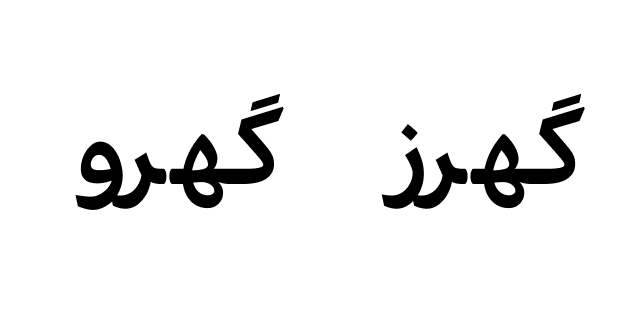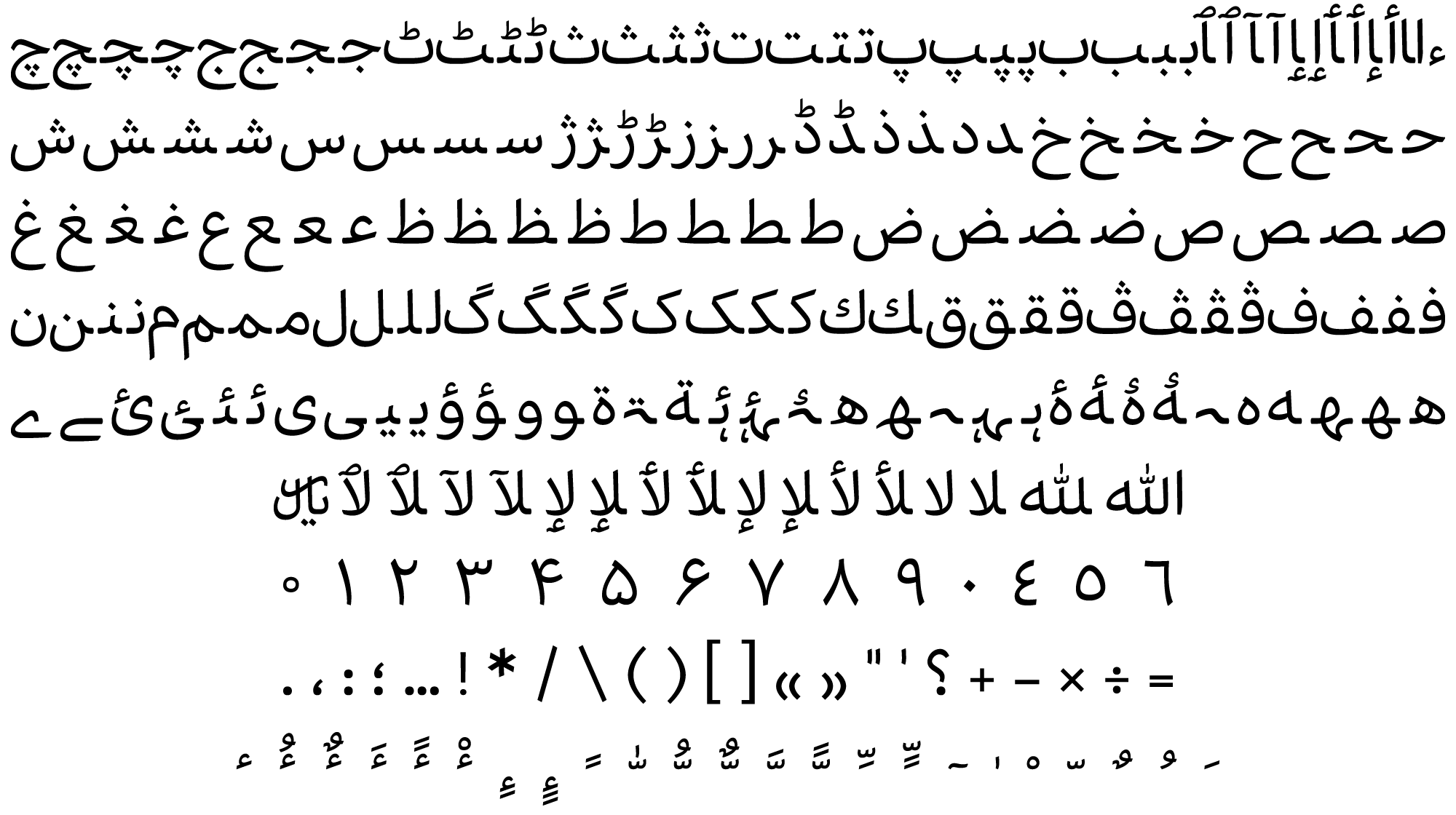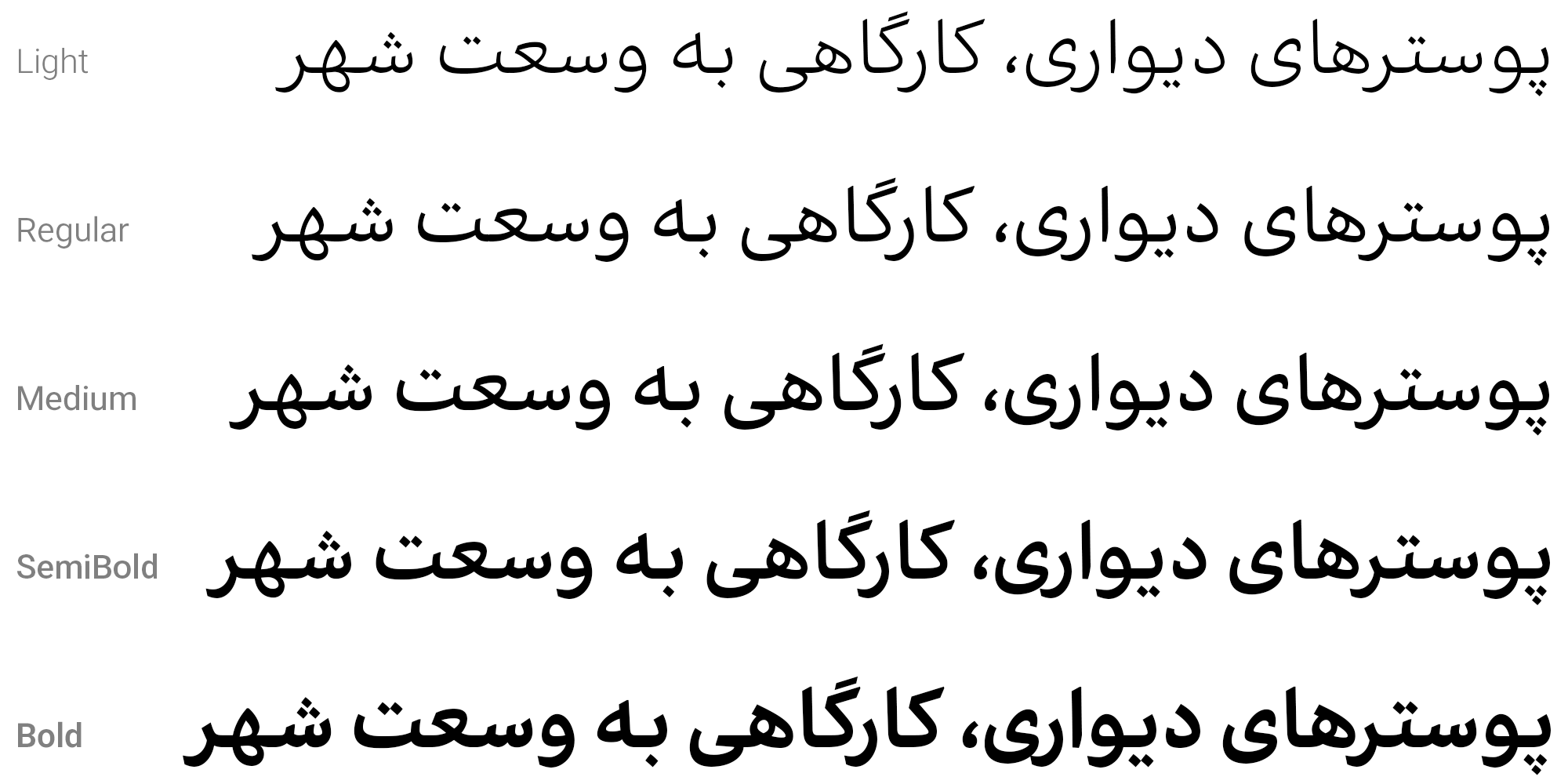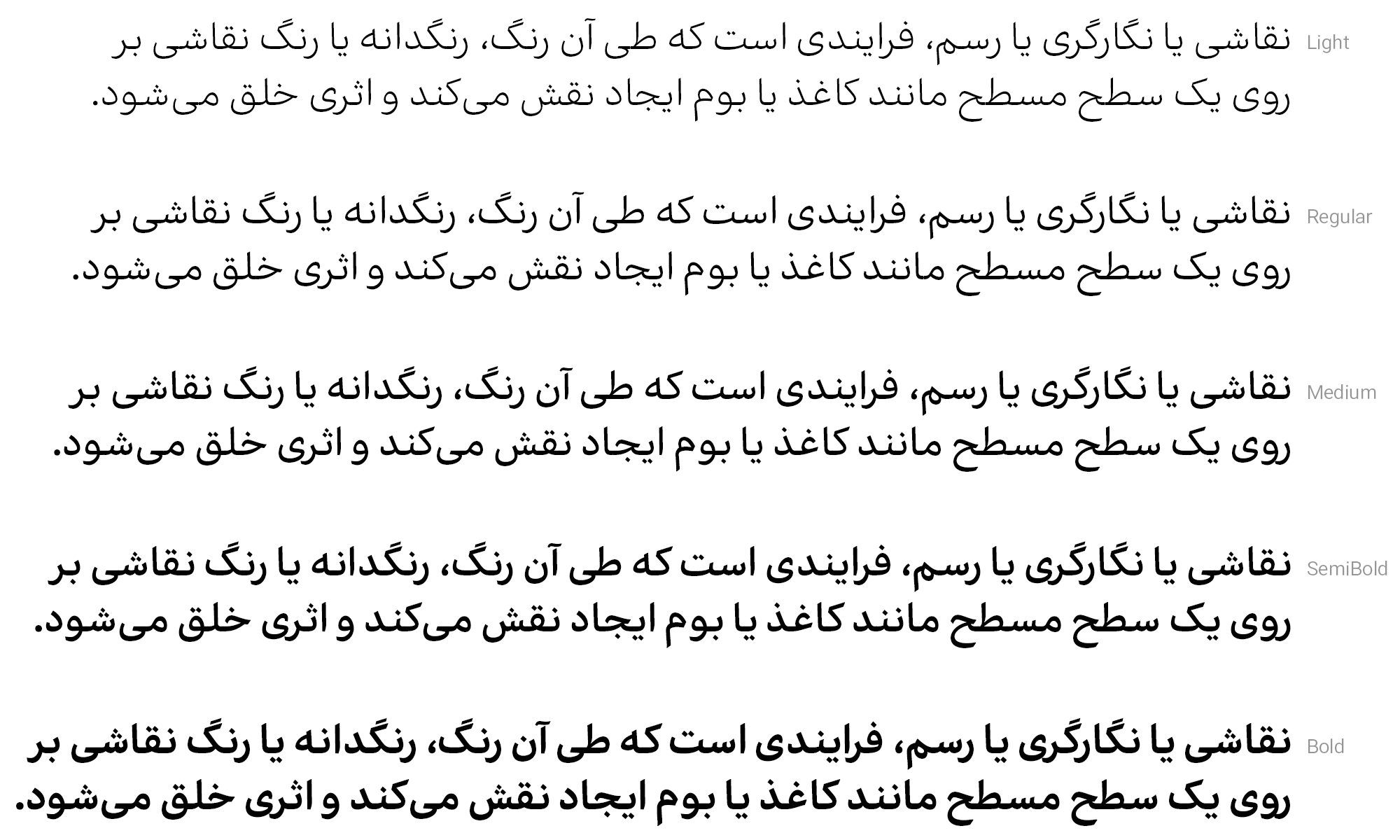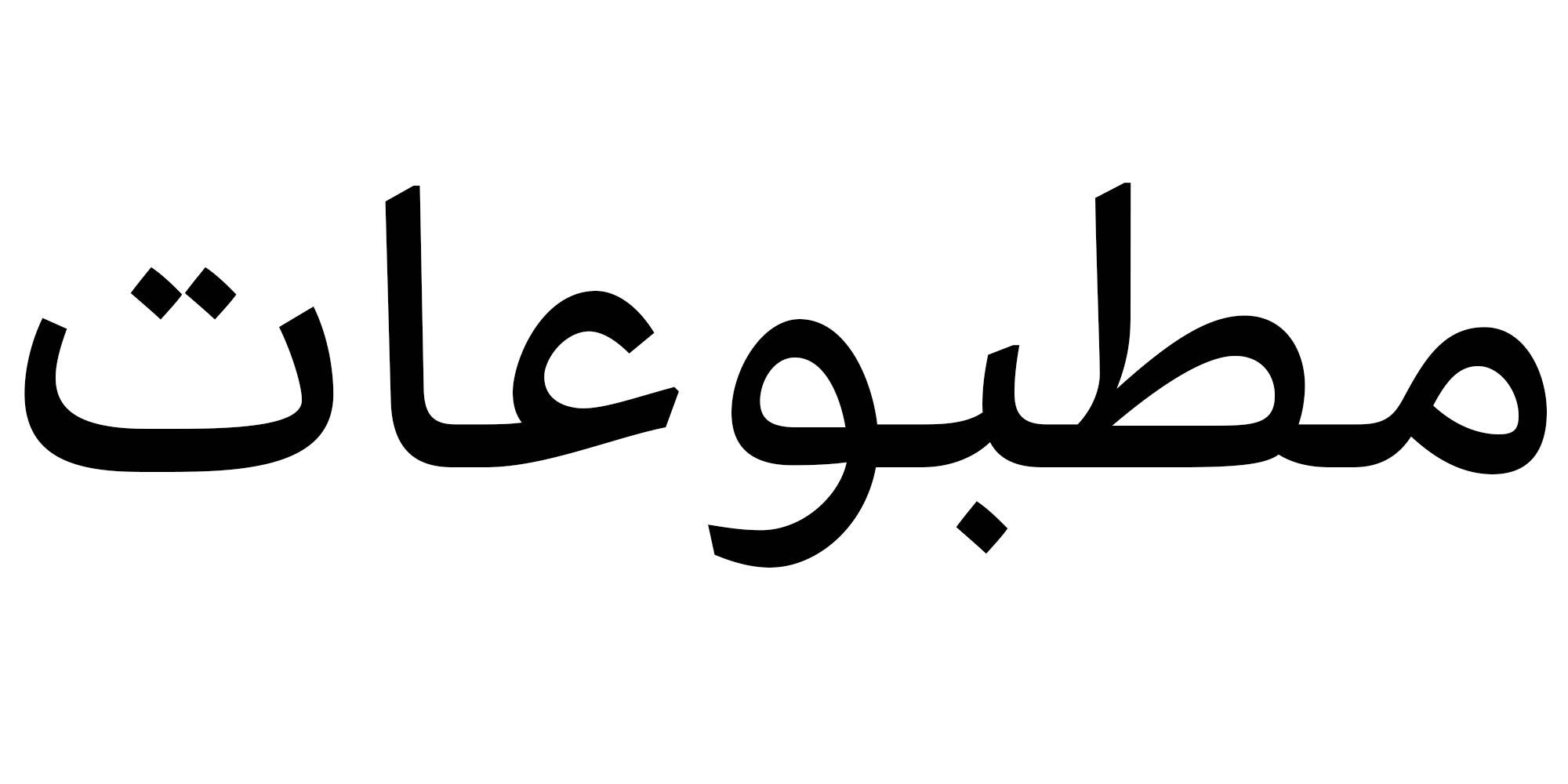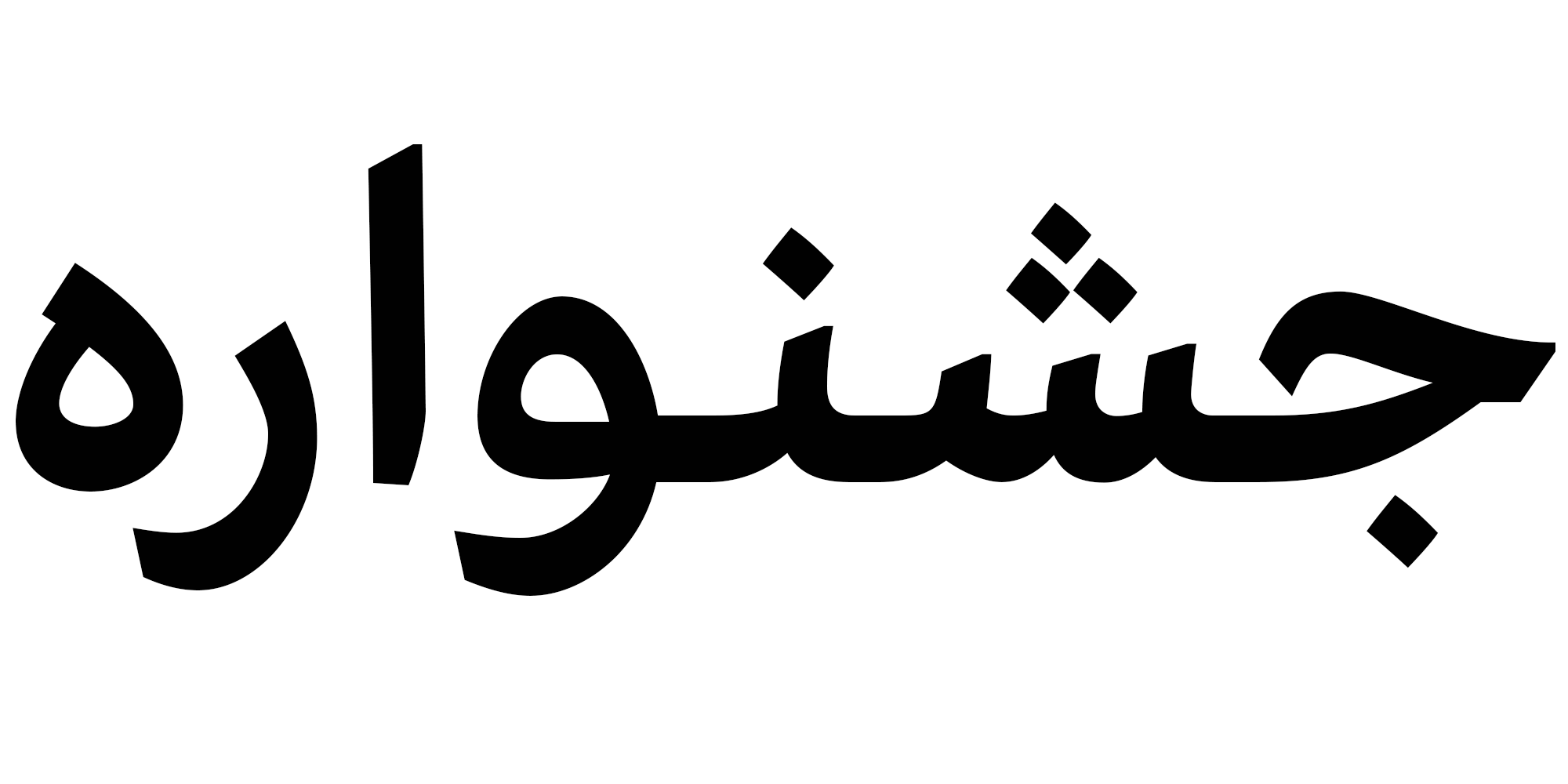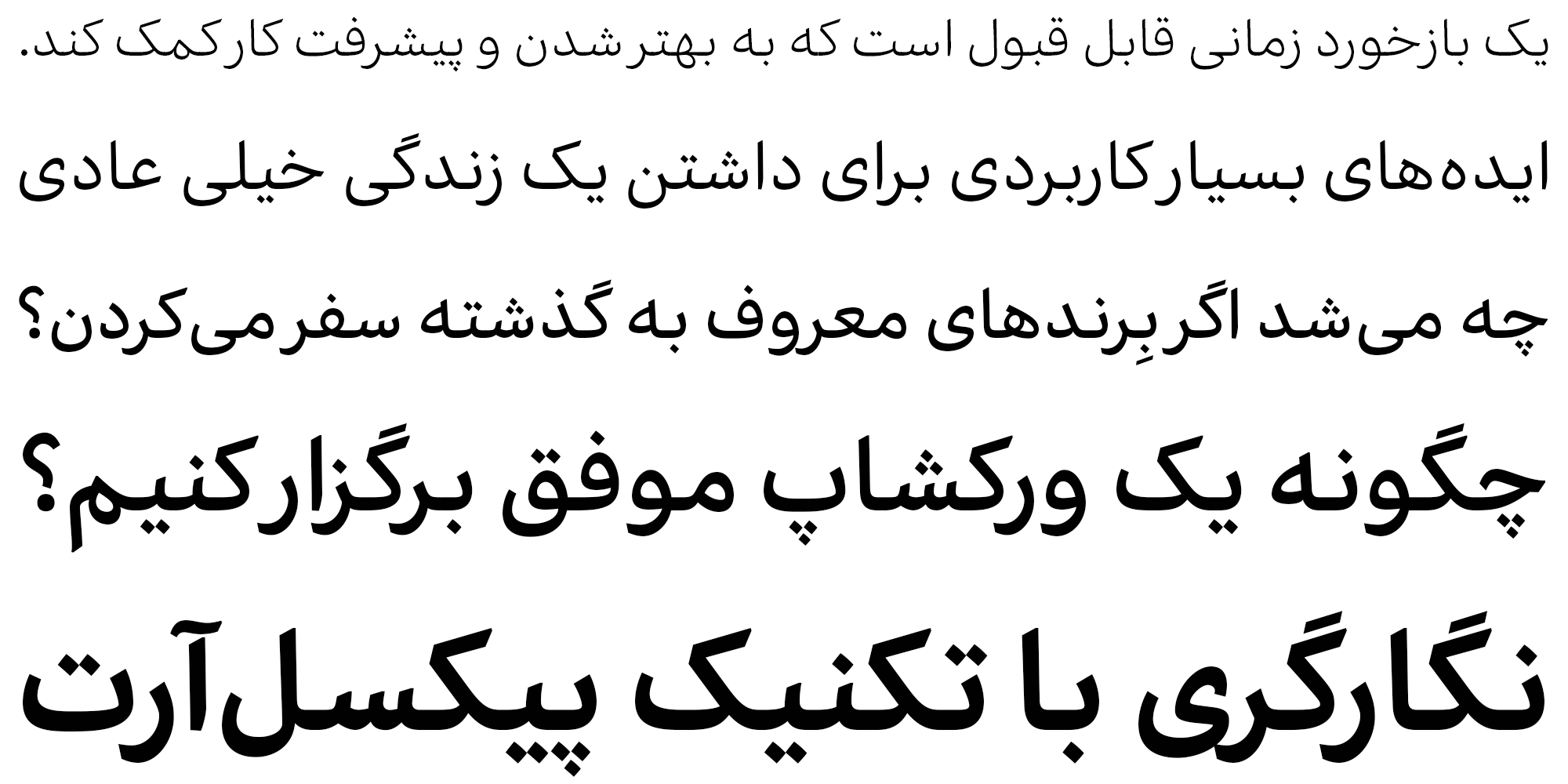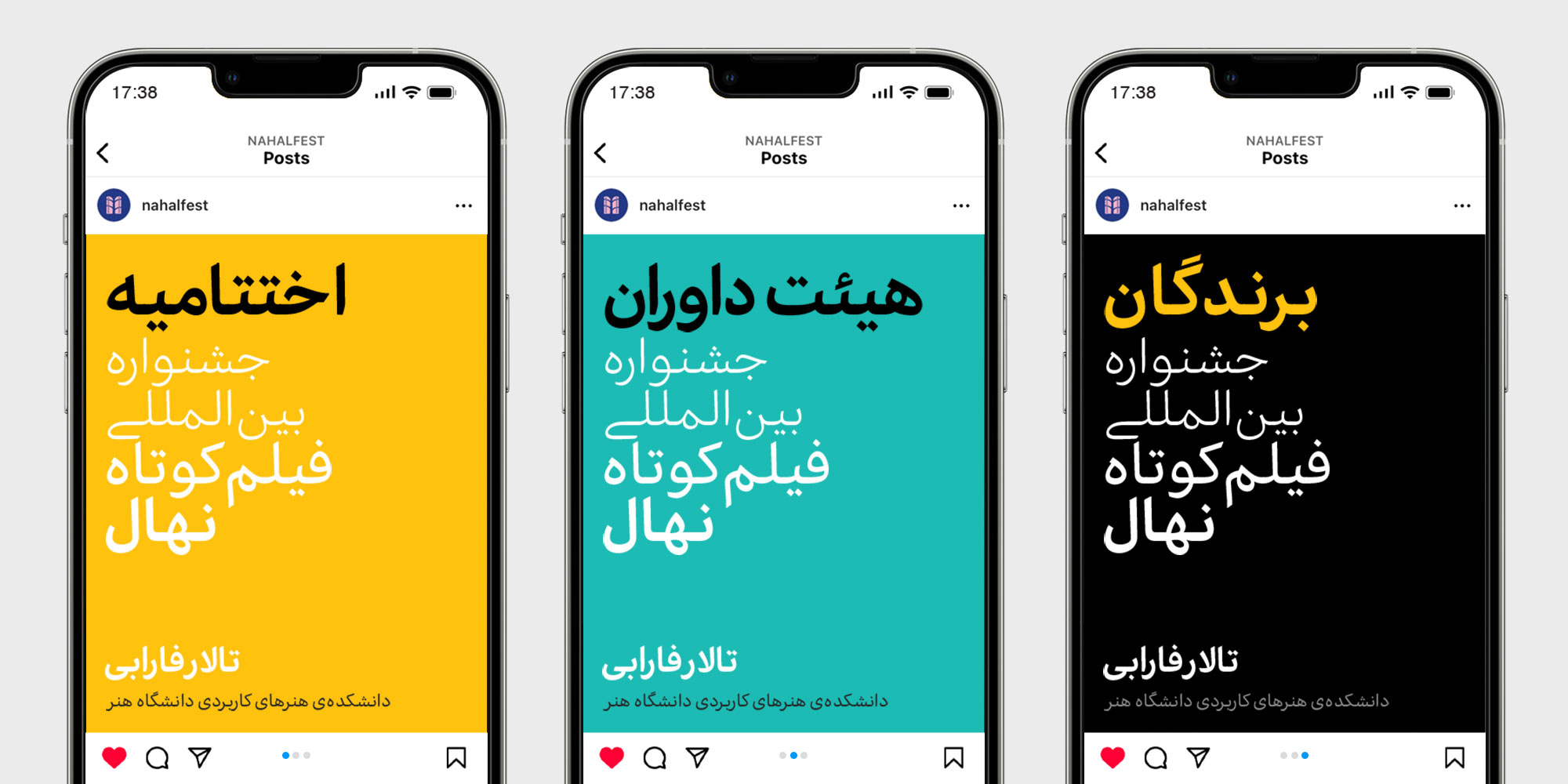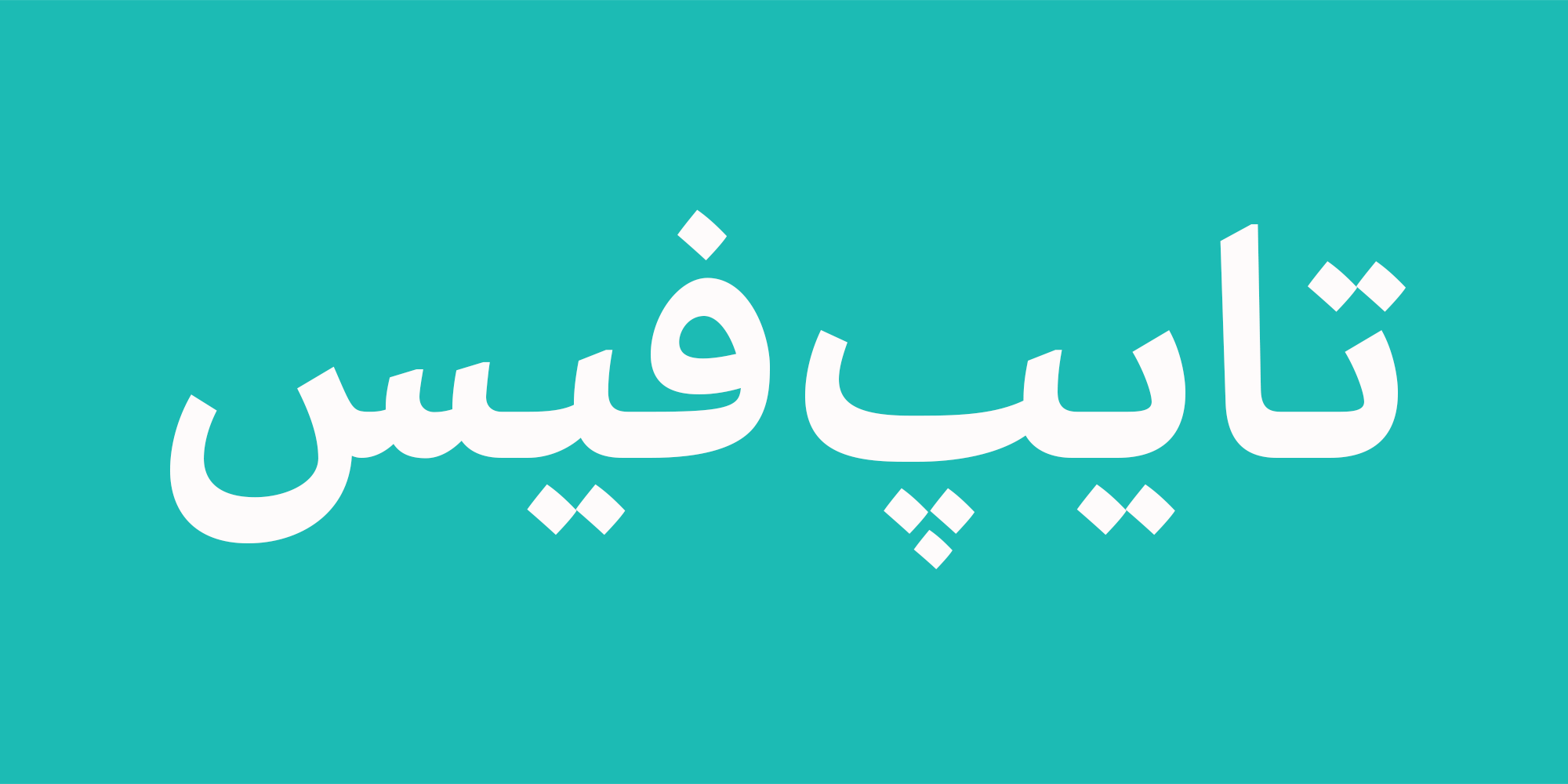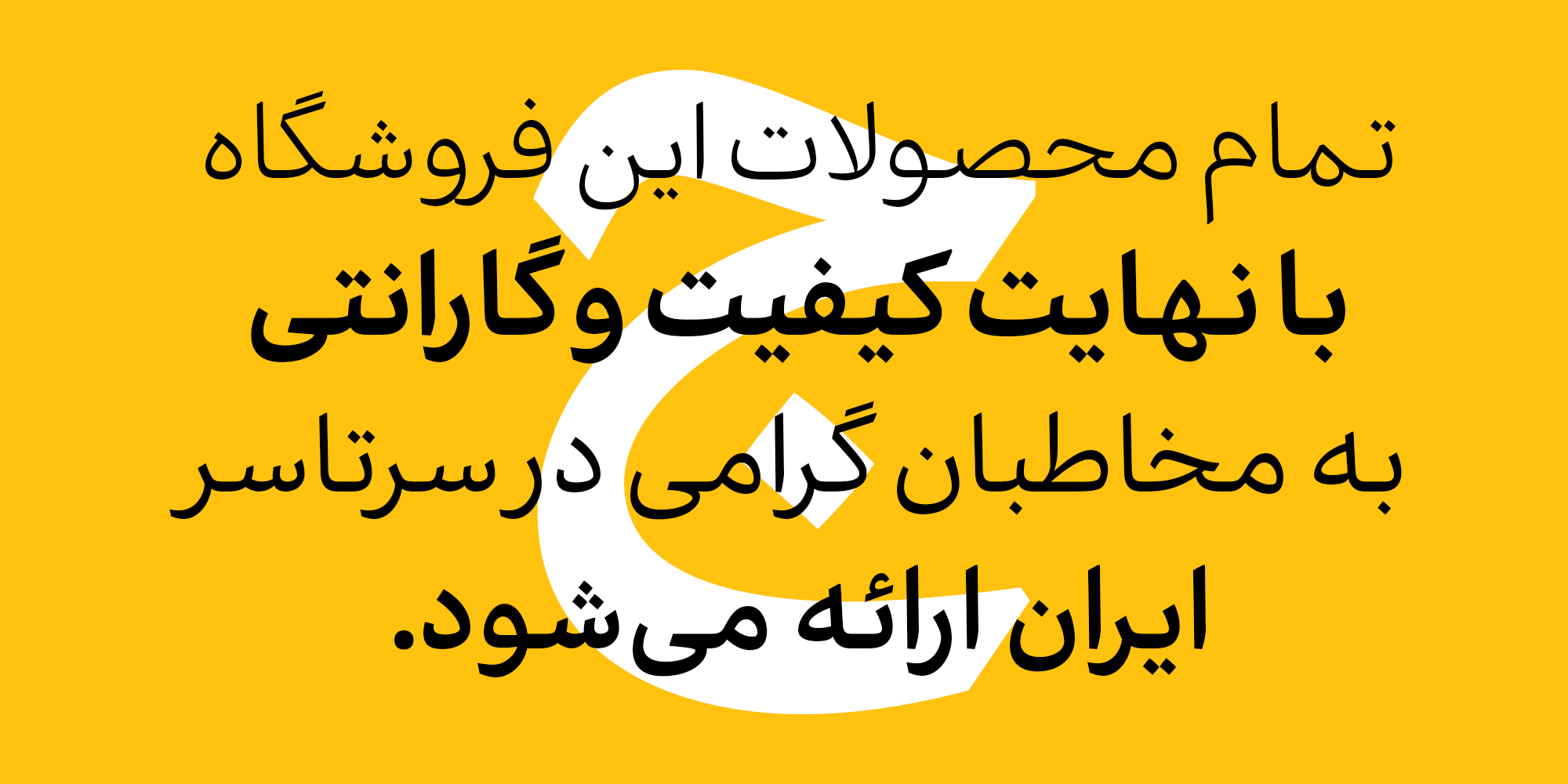
مشکل اتصال "ه" و "ز"، "ر" در بعضی از ترکیب ها
فونت اکران در ۵ وزن لایت، رگولار، مدیوم، سمی بولد و بولد موجود است. هر ۵ وزن فونت شامل گلیفهای لاتین هستند و دریک قلم منفرد میشود متن را در هر دو زبان لاتین و فارسی تنظیم کرد.
یکی از ویژگیهای منحصر به فرد این فونت، قابلیت استفاده در صفحه نمایشهای با وضوح پائین بدون از دست دادن خوانایی است. بنابراین چه در حال تماشای یک بازی فوتبال با یک دستگاه تلفن همراه کوچک یا یک صفحه تلویزیون بزرگ باشید، می توانید از حس خوشنویسانهی زیبای این فونت لذت ببرید.
اگر به دنبال یک تایپفیس شیک و مدرن هستید، جای دیگری دنبال این فونت زیبای فارسی نروید. با طراحی خیره کننده و همه فن حریف، انتخاب مناسبی برای هر کسی است که به دنبال اضافه کردن حسی جدید به متون خود است. امروز آن را امتحان کنید و خودتان تفاوت را ببینید!